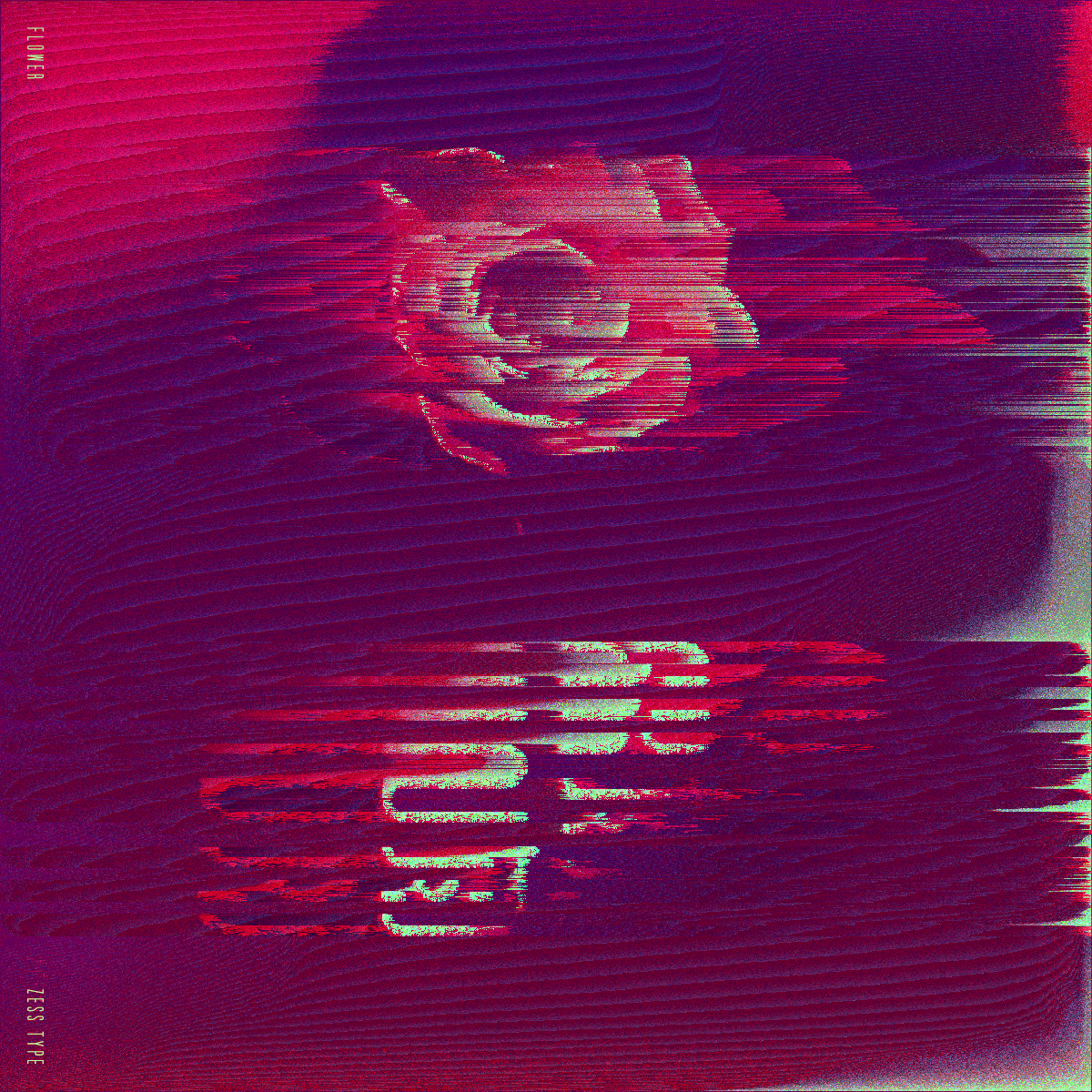
꽃피는들판 - 픽셀소팅
ZESSTYPE LETTERING WORK 2017
글리치 아트. Glitch Art - pixel sorting and databending 작업을 처음 해보았다. 다양한 방식으로 작업을 해왔지만. 새로운 방식은 역시 재미있다. 글자를 가지고 작업했지만 전혀 읽을 수 없는 작업.Processing 툴을 사용했는데 코드로 이루어져있어서 전혀 1도 모르겠지만.아무튼 이것저것 눌러보니 결과물이 나온다.그 결과물들을 레이어로 쌓아 이래저래 오버랩하여 하나의 이미지로 섞었다. 원하는 이미지에 가까워질 때까지 섞고 또 섞었다. 이미지 믹싱. 아이디어가 1도 떠오르지 않을 때 아주 괜찮은 작업 방식을 찾았다.원하는대로 능숙하게 다루긴 어렵겠지만.이것저것 눌러보는 재미가 있으니 뭐.그럭저럭 만족한다.